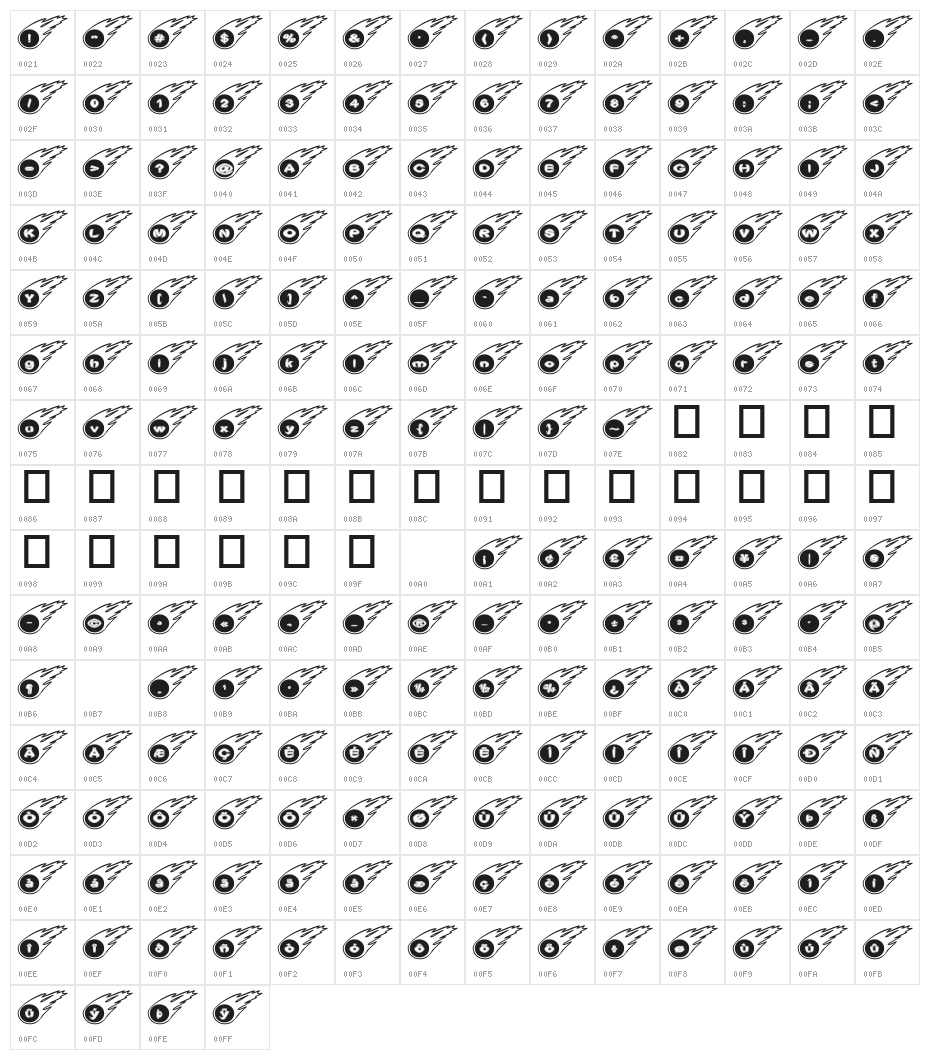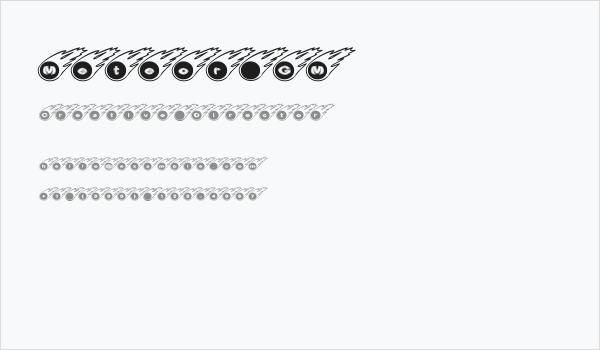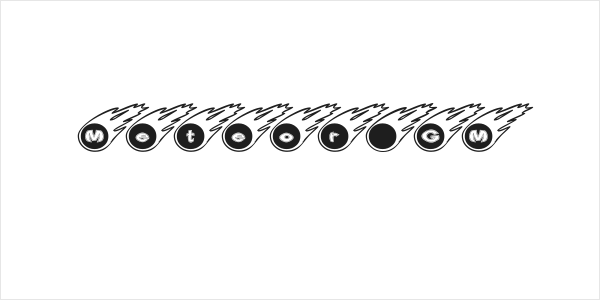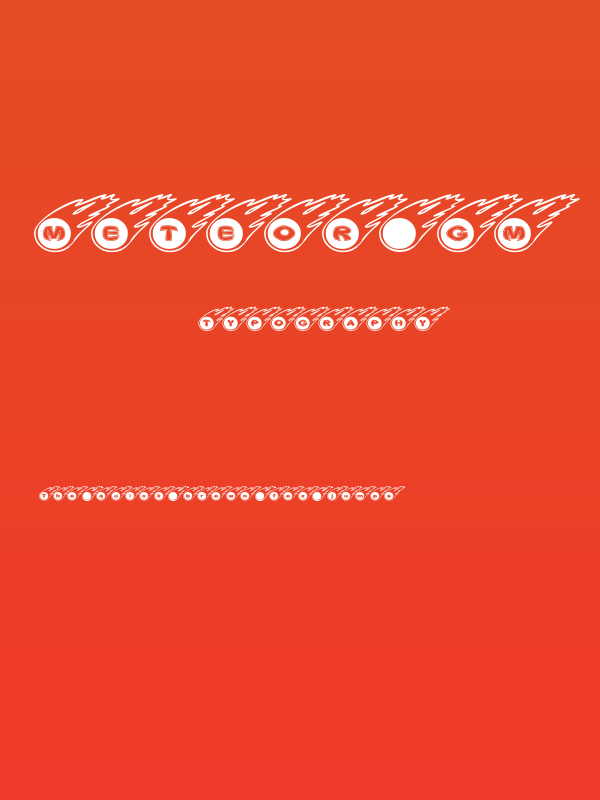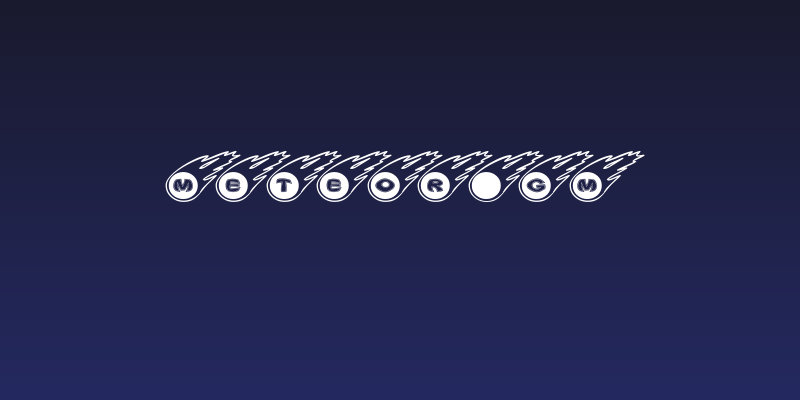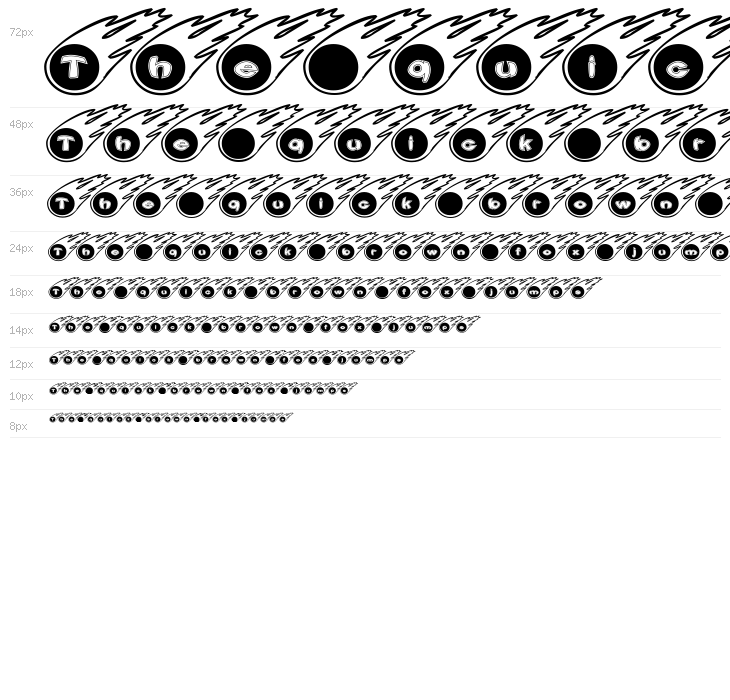
Meteor GM Font
| Progetti proposti | Ideal for children's book covers, event posters, video game titles, and any project needing a playful and dynamic touch. |